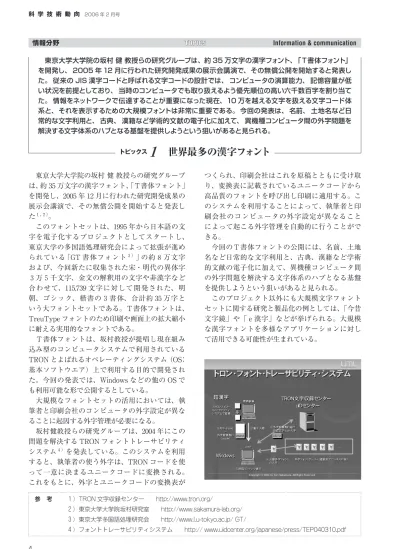
東京大学大学院の坂村 健 教授らの研究グループは、約 35 万文字の漢字フォント、「T書体フォント」
を開発し、 2005 年 12 月に行われた研究開発成果の展示会講演で、その無償公開を開始すると発表し た。 従来の JIS 漢字コードと呼ばれる文字コードの設計では、 コンピュータの演算能力、 記憶容量が低 い状況を前提としており、 当時のコンピュータでも取り扱えるよう優先順位の高い六千数百字を割り当て た。 情報をネットワークで伝達することが重要になった現在、10 万を越える文字を扱える文字コード体 系と、それを表示するための大規模フォントは非常に重要である。 今回の発表は、 名前、 土地名など日 常的な文字利用と、 古典、 漢籍など学術的文献の電子化に加えて、 異機種コンピュータ間の外字問題を 解決する文字体系のハブとなる基盤を提供しようという狙いがあると見られる。
東京大学大学院の坂村 健 教授らの研究グループ は、約 35 万文字の漢字フォント、 「T書体フォント」
を開発し、2005 年 12 月に行われた研究開発成果の 展示会講演で、その無償公開を開始すると発表し た
1、2)。
このフォントセットは、1995 年から日本語の文 字を電子化するプロジェクトとしてスタートし、
東京大学の多国語処理研究会によって拡張が進め られている 「GT 書体フォント
3)」 の約8万文字 および、今回新たに収集された宋・明代の異体字 3万5千文字、金文の解釈用の文字や非漢字など 合わせて、115,739 文字に対して開発された、明 朝、ゴシック、楷書の3書体、合計約 35 万字と いう大フォントセットである。T書体フォントは、
TreuType フォントのため印刷や画面上の拡大縮小 に耐える実用的なフォントである。
T書体フォントは、坂村教授が提唱し現在組み 込み型のコンピュータシステムで利用されている TRON とよばれるオペレーティングシステム(OS:
基本ソフトウエア)上で利用する目的で開発され た。今回の発表では、Windows などの他の OS で も利用可能な形で公開するとしている。
大規模なフォントセットの活用においては、執 筆者と印刷会社のコンピュータの外字設定が異な ることに起因する外字管理が必要になる。
坂村健教授らの研究グループは、2004 年にこの 問題を解決する TRON フォントトレーサビリティ システム
4)を発表している。このシステムを利用 すると、執筆者の使う外字は、TRON コードを使 って一意に決まるユニークコードに変換される。
これをもとに、外字とユニークコードの変換表が
つくられ、印刷会社はこれを原稿とともに受け取 り、変換表に記載されているユニークコードから 高品質のフォントを呼び出し印刷に適用する。こ のシステムを利用することによって、執筆者と印 刷会社のコンピュータの外字設定が異なること によって起こる外字管理を自動的に行うことがで きる。
今回のT書体フォントの公開には、名前、土地 名など日常的な文字利用と、古典、漢籍など学術 的文献の電子化に加えて、異機種コンピュータ間 の外字問題を解決する文字体系のハブとなる基盤 を提供しようという狙いがあると見られる。
このプロジェクト以外にも大規模文字フォント セットに関する研究と製品化の例としては、「今昔 文字鏡」や「e漢字」などが挙げられる。大規模 な漢字フォントを多様なアプリケーションに対し て活用できる可能性が生まれている。
世界最多の漢字フォント